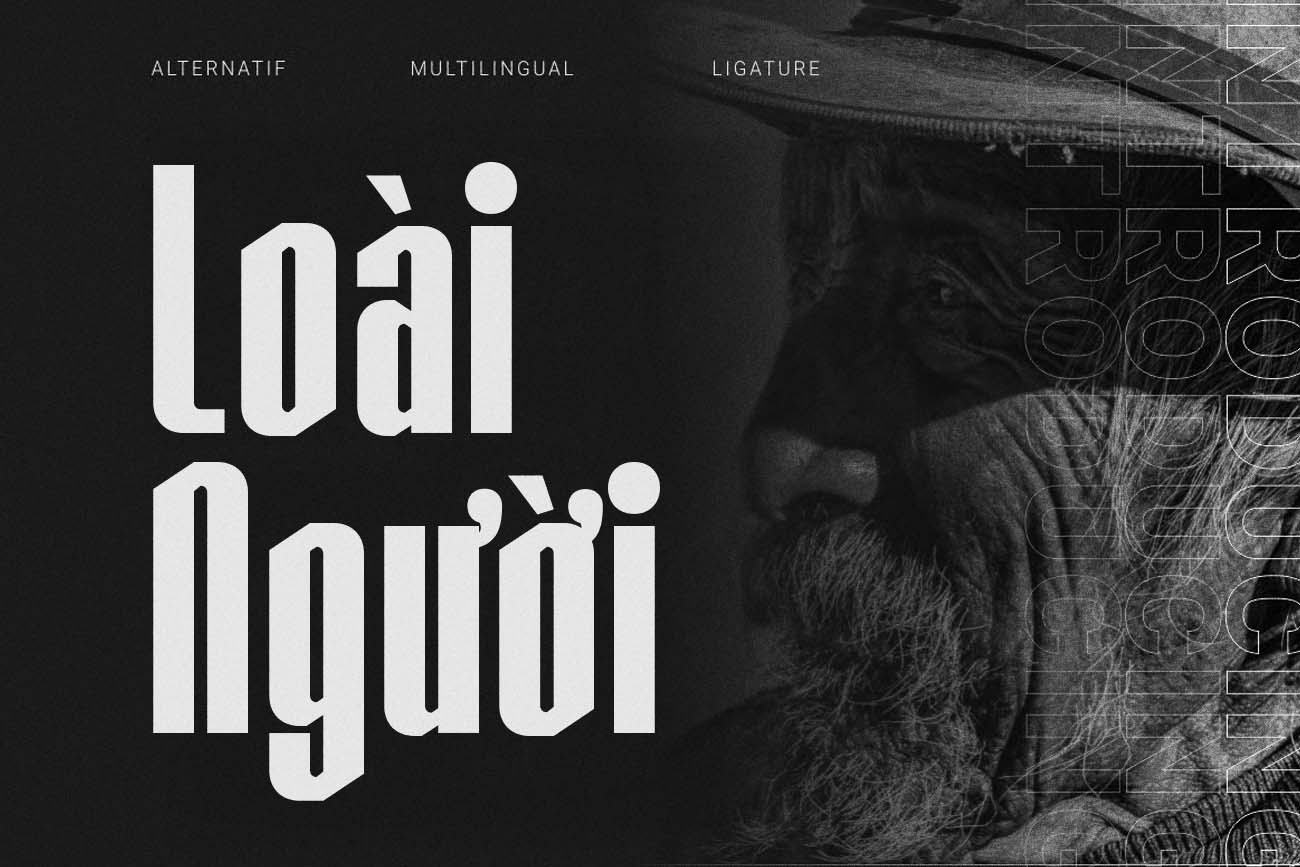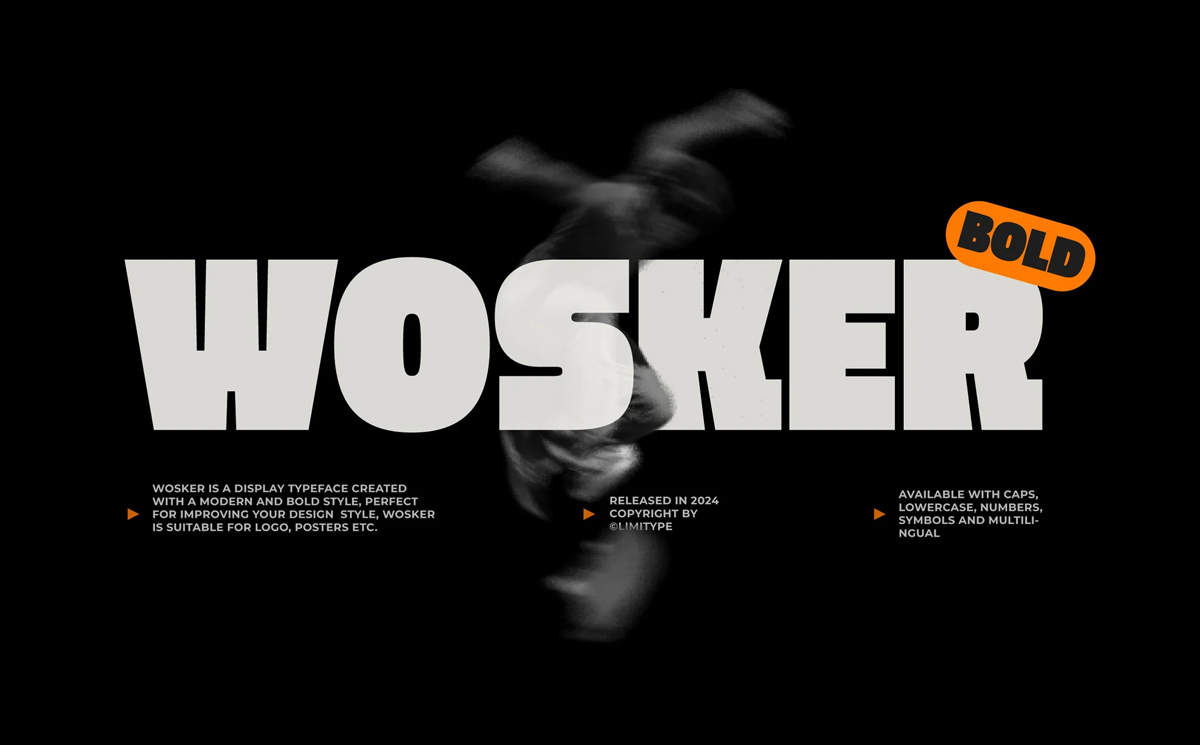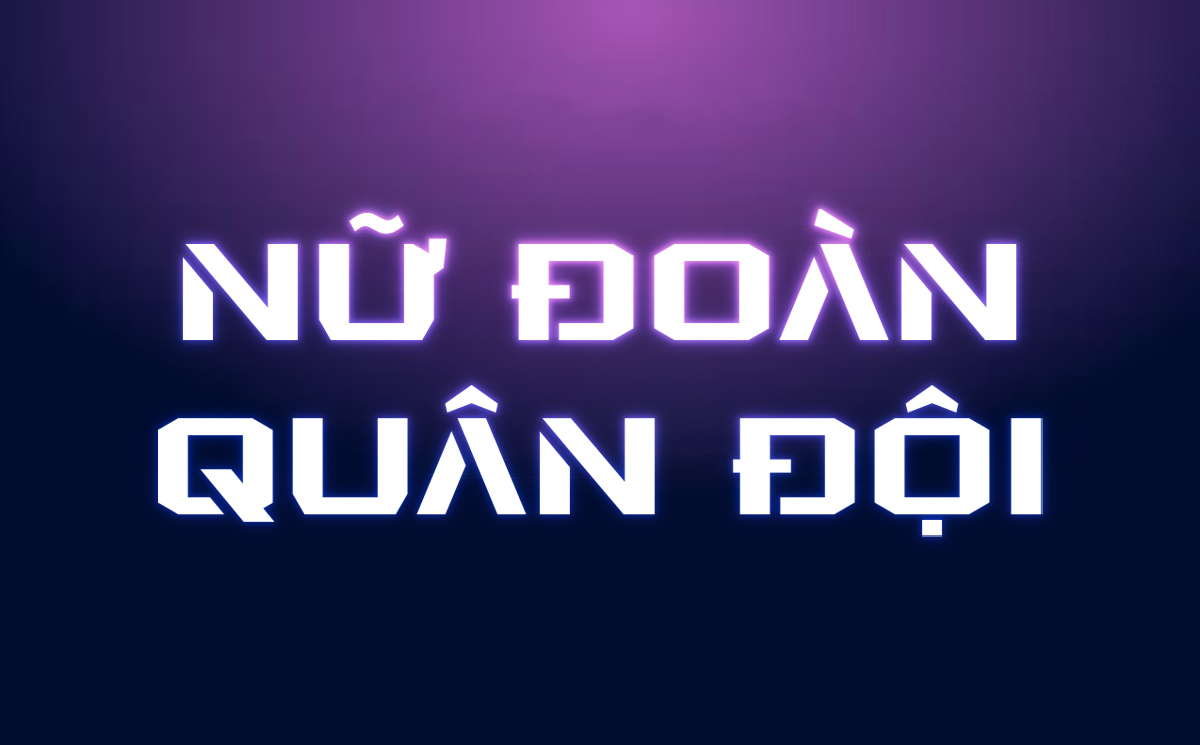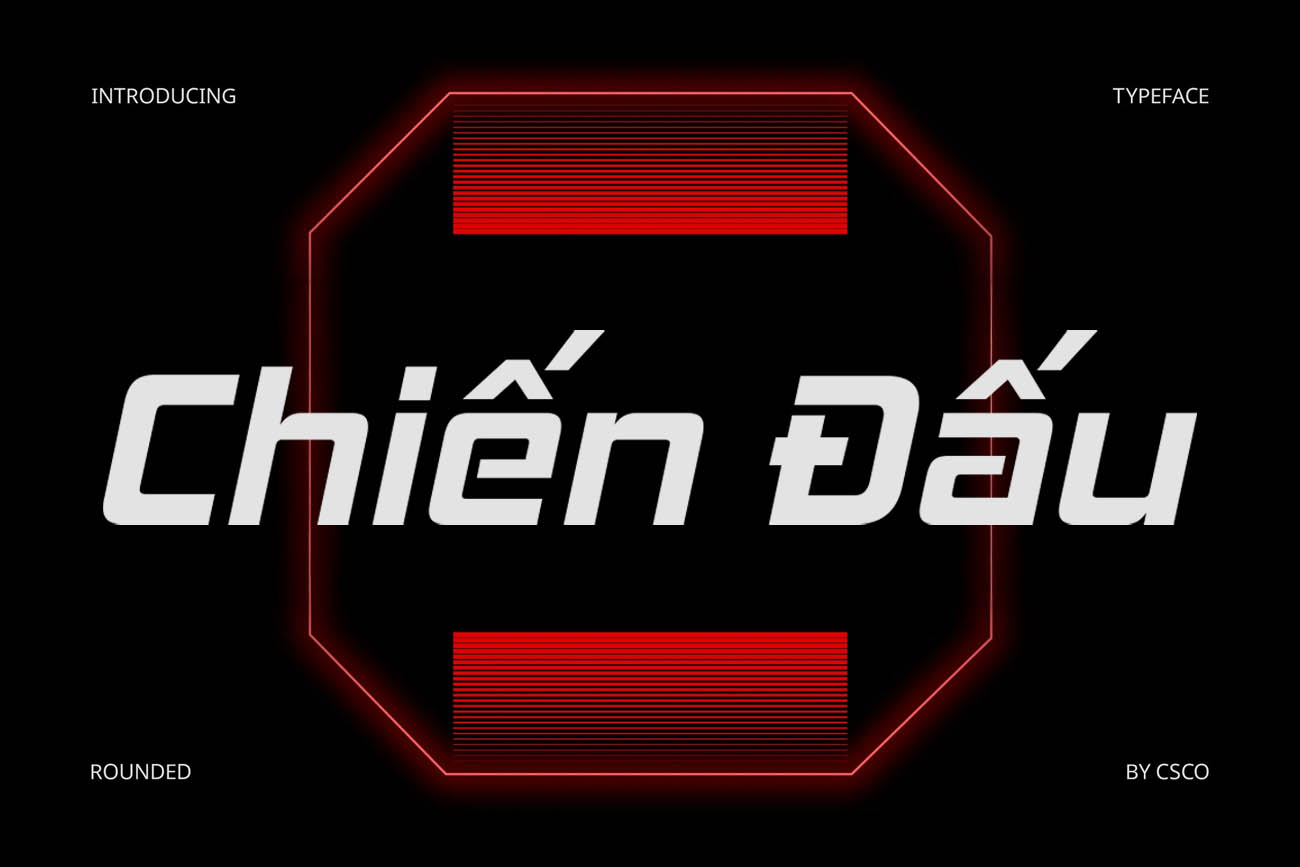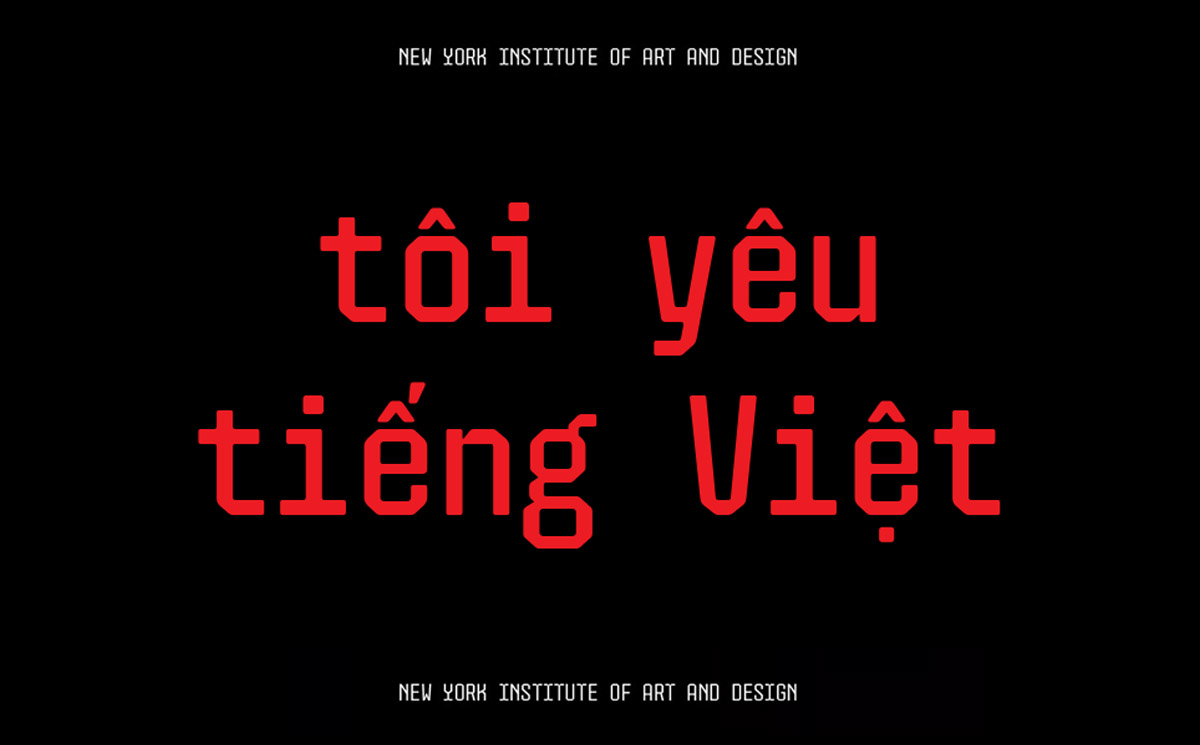
Font chữ cho esports, livestream overlay và poster giải đấu
Gợi ý 15 font TH Việt hóa mạnh mẽ cho esports, livestream overlay, poster giải đấu, thumbnail gaming và banner social.
Thiết kế eSport có một áp lực khác hẳn các ngành thương hiệu thông thường: chữ phải mạnh, nhanh, dễ nhận ra trong vài giây và vẫn đọc tốt trên màn hình livestream. Một poster giải đấu có thể dùng font rất dữ, nhưng overlay stream lại cần font gọn hơn để bảng điểm, tên đội, tên caster và thông số trận không bị rối. Vì vậy, chọn font cho eSport không chỉ là chọn “font gaming đẹp”, mà là xây một hệ thống chữ dùng được từ poster đến broadcast.
Bài viết này gợi ý 15 font TH Việt hóa phù hợp cho eSport, livestream overlay, poster giải đấu, thumbnail gaming và banner social. Danh sách ưu tiên các font thể thao, công nghệ, sans-serif cứng cáp và display mạnh. Anh có thể dùng một font làm title chính, một font làm UI phụ, rồi thêm hiệu ứng stroke, glow, bevel hoặc shadow tùy phong cách giải.
Chọn font esports cần chú ý điều gì?
Đầu tiên là độ đọc ở kích thước nhỏ. Overlay livestream thường có nhiều vùng chữ nhỏ: tên đội, tỉ số, bản đồ, timer, caster, vòng đấu, sponsor. Nếu font quá trang trí, khán giả xem trên điện thoại sẽ khó nắm thông tin. Thứ hai là tính nhận diện. Poster trận đấu, lịch thi đấu và banner công bố đội hình cần font đủ cá tính để người xem nhớ ngay mood của giải. Thứ ba là hỗ trợ tiếng Việt có dấu, vì các cụm như “Vòng loại”, “Bán kết”, “Chung kết”, “Đội hình thi đấu”, “Lịch livestream” rất dễ lộ lỗi dấu nếu font không xử lý tốt.
Top 15 font TH cho esports, stream overlay và poster giải đấu
1. TH Neo Cybern - logo đội, poster trận đấu và key visual giải eSport
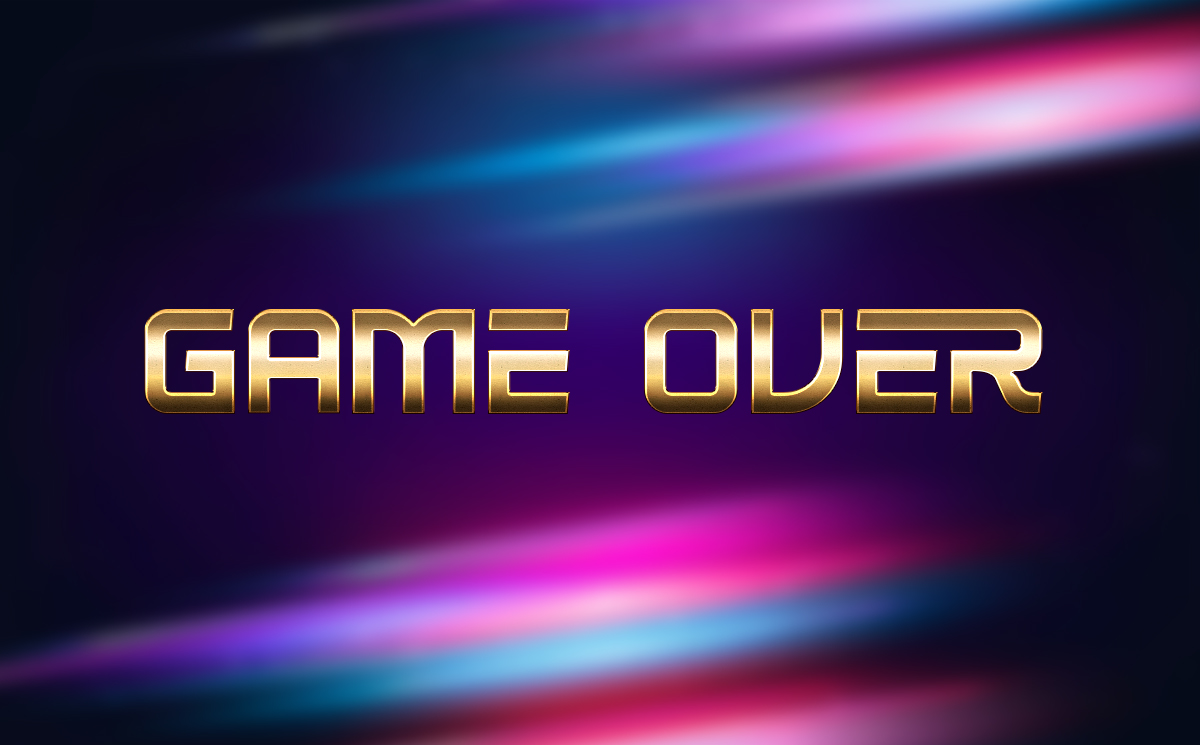
Tải font TH Neo Cybern nếu anh đang làm logo đội, poster trận đấu và key visual giải eSport. Điểm mạnh của TH Neo Cybern là hình khối hiện đại, chất cyber rõ, tạo cảm giác cạnh tranh và công nghệ ngay từ tiêu đề. Với eSport, font này nên dùng ở các cụm chữ có tính kêu gọi hoặc thông báo nhanh như “Chung kết”, “Đại chiến”, “Mở đăng ký”, “Đội hình ra sân”, “Live tối nay” hoặc tên series giải đấu.
Khi đưa vào thiết kế thực tế, anh nên test font trên ba kích thước: poster lớn, thumbnail social và overlay livestream 1080p. Nếu chữ vẫn rõ khi thu nhỏ, có thể dùng cho bảng tên và lower-third; nếu chỉ đẹp ở cỡ lớn, hãy giữ nó cho title, logo event hoặc màn hình chờ stream.
2. TH Striger - poster giải đấu, bảng lịch thi đấu và banner chiến thắng
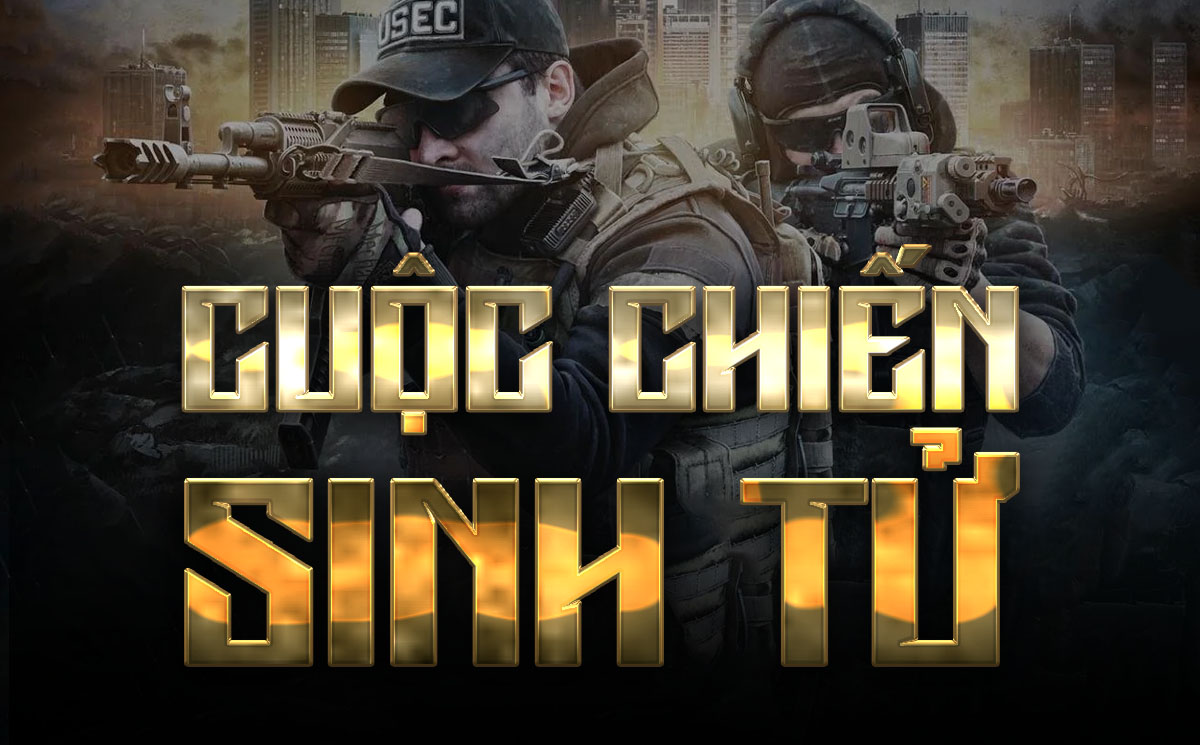
Tải font TH Striger nếu anh đang làm poster giải đấu, bảng lịch thi đấu và banner chiến thắng. Điểm mạnh của TH Striger là nét chữ mạnh, gọn và có tinh thần thể thao, dễ nổi bật trên nền ảnh game hoặc ảnh tuyển thủ. Với eSport, font này nên dùng ở các cụm chữ có tính kêu gọi hoặc thông báo nhanh như “Chung kết”, “Đại chiến”, “Mở đăng ký”, “Đội hình ra sân”, “Live tối nay” hoặc tên series giải đấu.
Khi đưa vào thiết kế thực tế, anh nên test font trên ba kích thước: poster lớn, thumbnail social và overlay livestream 1080p. Nếu chữ vẫn rõ khi thu nhỏ, có thể dùng cho bảng tên và lower-third; nếu chỉ đẹp ở cỡ lớn, hãy giữ nó cho title, logo event hoặc màn hình chờ stream.
3. TH Bladus Slant - livestream countdown, highlight reel và thumbnail tốc độ
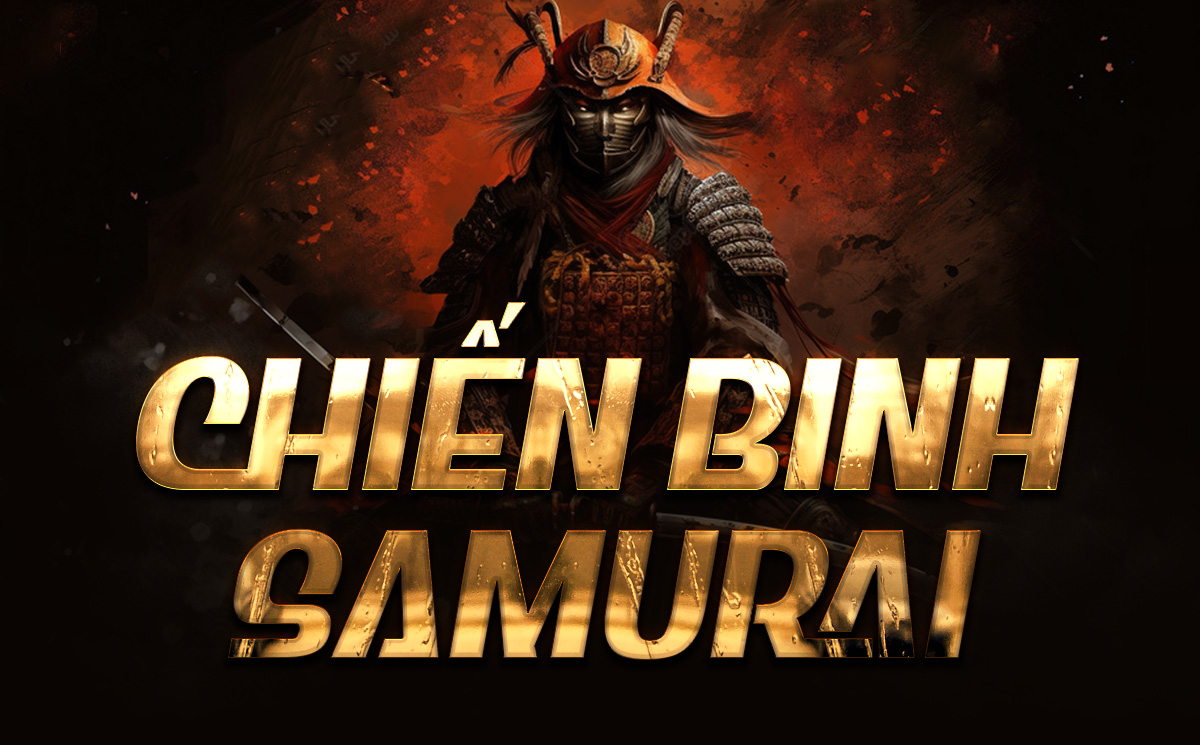
Tải font TH Bladus Slant nếu anh đang làm livestream countdown, highlight reel và thumbnail tốc độ. Điểm mạnh của TH Bladus Slant là dáng nghiêng tạo chuyển động, rất hợp với layout có vệt sáng, motion blur hoặc đường cắt chéo. Với eSport, font này nên dùng ở các cụm chữ có tính kêu gọi hoặc thông báo nhanh như “Chung kết”, “Đại chiến”, “Mở đăng ký”, “Đội hình ra sân”, “Live tối nay” hoặc tên series giải đấu.
Khi đưa vào thiết kế thực tế, anh nên test font trên ba kích thước: poster lớn, thumbnail social và overlay livestream 1080p. Nếu chữ vẫn rõ khi thu nhỏ, có thể dùng cho bảng tên và lower-third; nếu chỉ đẹp ở cỡ lớn, hãy giữ nó cho title, logo event hoặc màn hình chờ stream.
4. TH Bringas - title poster, thông báo đội hình và banner đối đầu
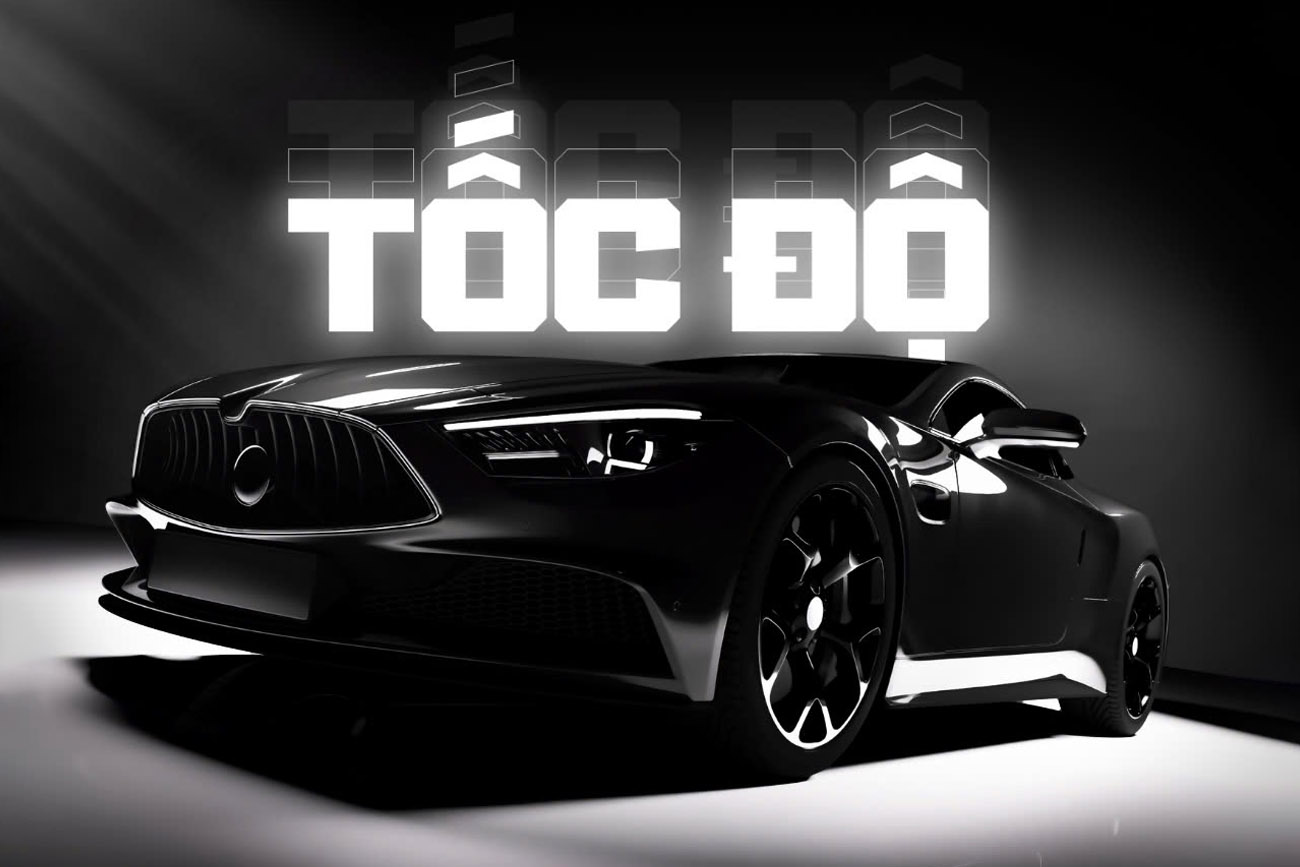
Tải font TH Bringas nếu anh đang làm title poster, thông báo đội hình và banner đối đầu. Điểm mạnh của TH Bringas là chữ dày, khỏe, dễ tạo cảm giác “versus” khi đặt cạnh ảnh hai đội hoặc hai nhân vật. Với eSport, font này nên dùng ở các cụm chữ có tính kêu gọi hoặc thông báo nhanh như “Chung kết”, “Đại chiến”, “Mở đăng ký”, “Đội hình ra sân”, “Live tối nay” hoặc tên series giải đấu.
Khi đưa vào thiết kế thực tế, anh nên test font trên ba kích thước: poster lớn, thumbnail social và overlay livestream 1080p. Nếu chữ vẫn rõ khi thu nhỏ, có thể dùng cho bảng tên và lower-third; nếu chỉ đẹp ở cỡ lớn, hãy giữ nó cho title, logo event hoặc màn hình chờ stream.
5. TH Cungcap 13 - giải đấu có phong cách retro, poster mùa giải và merch cộng đồng
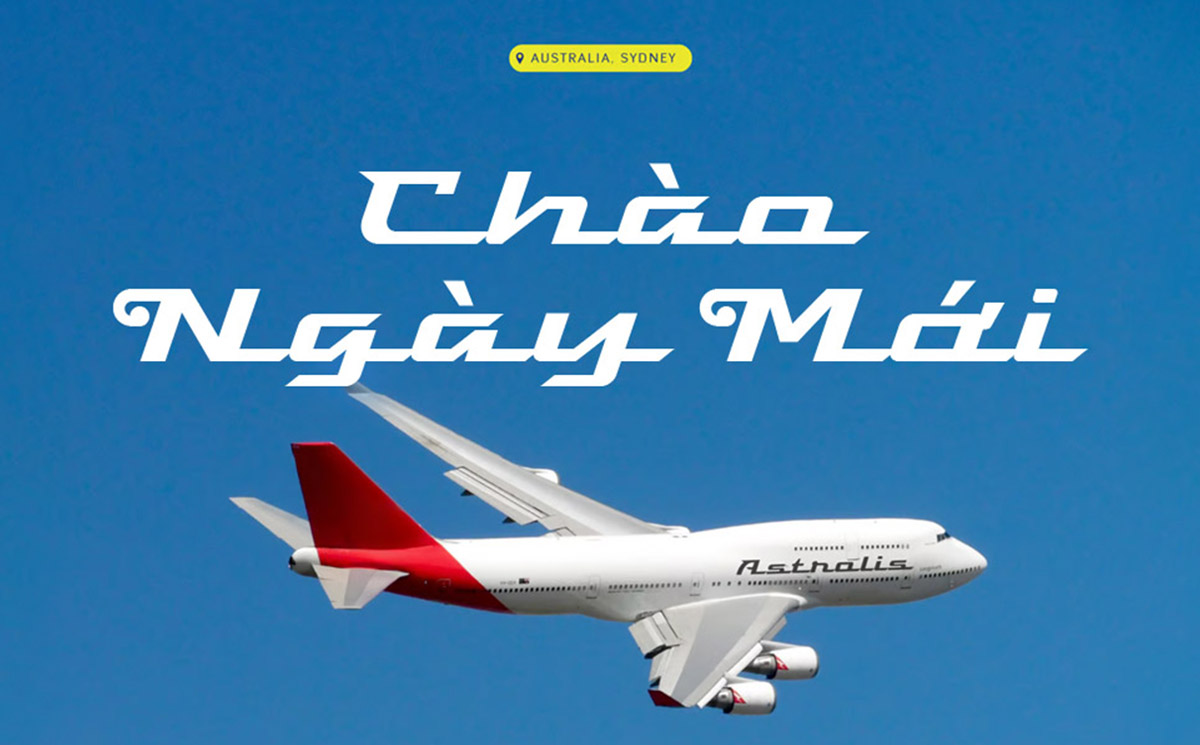
Tải font TH Cungcap 13 nếu anh đang làm giải đấu có phong cách retro, poster mùa giải và merch cộng đồng. Điểm mạnh của TH Cungcap 13 là vừa cứng cáp vừa có hơi vintage, hợp khi muốn eSport nhìn khác biệt hơn phong cách cyber quen thuộc. Với eSport, font này nên dùng ở các cụm chữ có tính kêu gọi hoặc thông báo nhanh như “Chung kết”, “Đại chiến”, “Mở đăng ký”, “Đội hình ra sân”, “Live tối nay” hoặc tên series giải đấu.
Khi chọn font cuối cùng, hãy đặt thử vào chính nội dung tiếng Việt của giải: “Lịch thi đấu”, “Bán kết tổng”, “Chung kết toàn quốc”, “Đăng ký đội ngay”, “Livestream 20:00”. Nếu font giữ được nhịp chữ, dấu không vỡ và vẫn nổi bật trên mobile, đó là lựa chọn đáng đưa vào bộ nhận diện eSport.